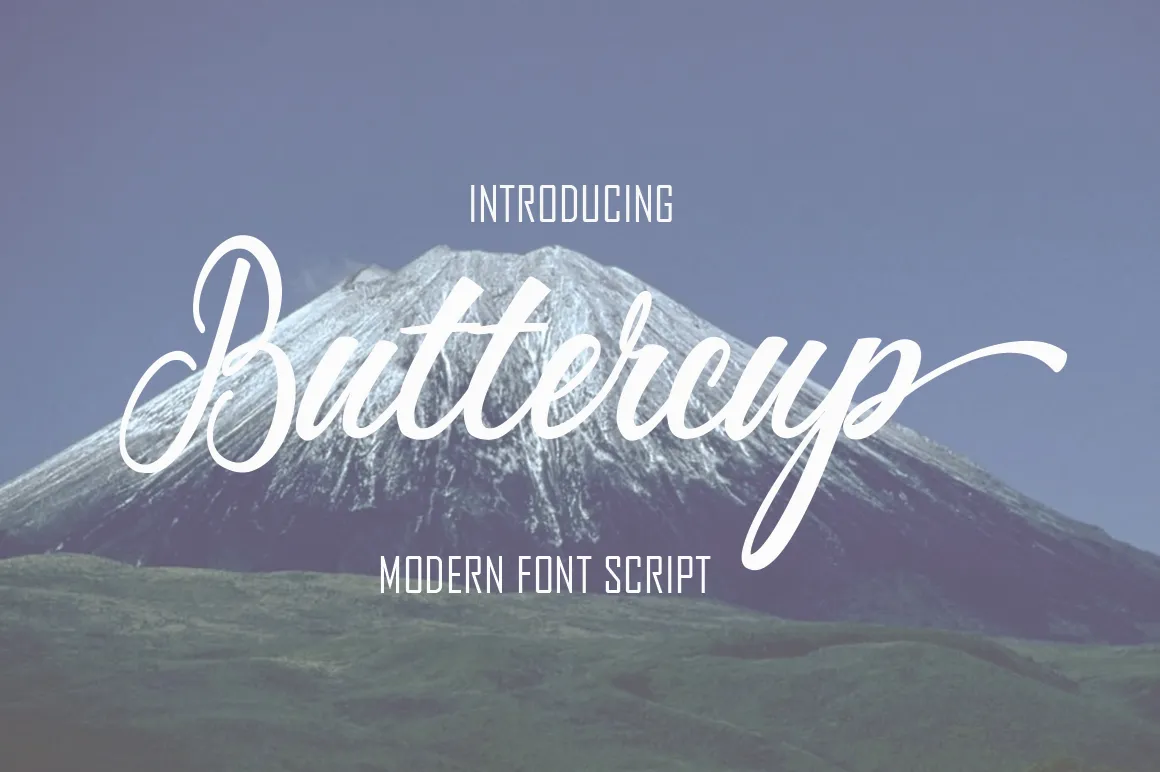
Buttercup Calligraphy Font – Download Grátis
A introdução do Buttercup Calligraphy Font é uma experiência única que vai transformar a maneira como você cria textos decorativos. Desenvolvida pelo designer polêm, este moderno e elegante estilo de letra foi criado para fornecer um visual encantador aos seus projetos. Com seu design cuidadosamente elaborado em estilo script moderno, o Buttercup Calligraphy Font é perfeito para uma variedade de aplicativos como cartões de mensagem, cabeçalhos de blog, impressões de pôster, logos de marca, embalagens de moda e até mesmo convites de aniversário. Este font não apenas oferece um aspecto atraente, mas também permite que você personalize o texto de maneira única para cada projeto, tornando-o uma opção versátil para designers, ilustradores e criativos em geral. O Buttercup Calligraphy Font é sua chave para criar textos ainda mais encantadores e personalizados nas suas próximas criações.